もじかけえほん かな?
偕成社は、秀親さん・塚田哲也さんの2人組「大日本タイポ組合」による「いぬ」が「かめ」といった一部が変わるだけで、別の文字・別の意味になる。タイポグラフィの面白さをしかけで表現する絵本「もじかけえほん かな?」を、2020年5月発売する。
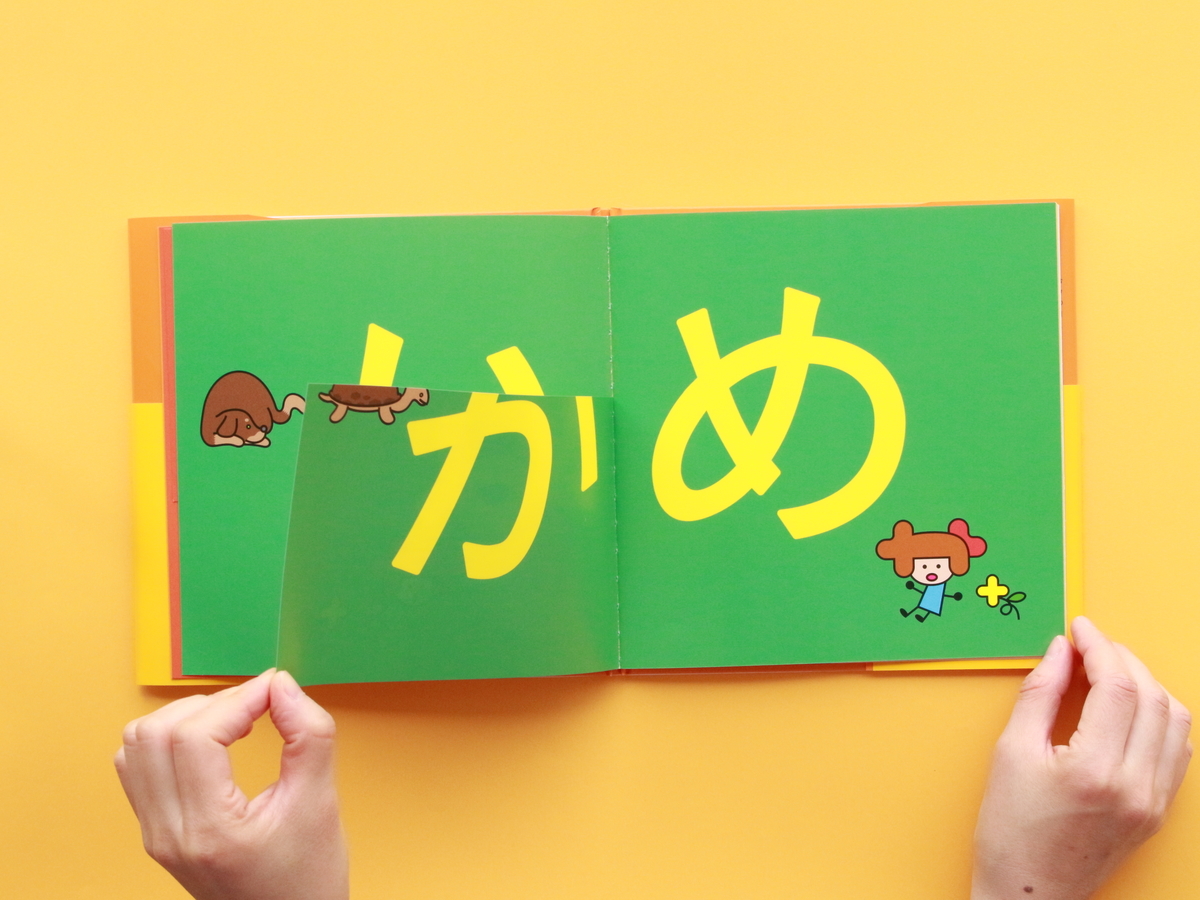
一瞬で文字と意味が変わる! 感覚で感じる面白さ「もじかけえほん かな?」
タイポグラフィの面白さを感覚的に表した絵本、『もじかけえほん かな?』。一部のページが縦や横の半分サイズになっているという、単純なしかけながら、めくるとあっと驚く変化が起こる。
たとえば「さら」。
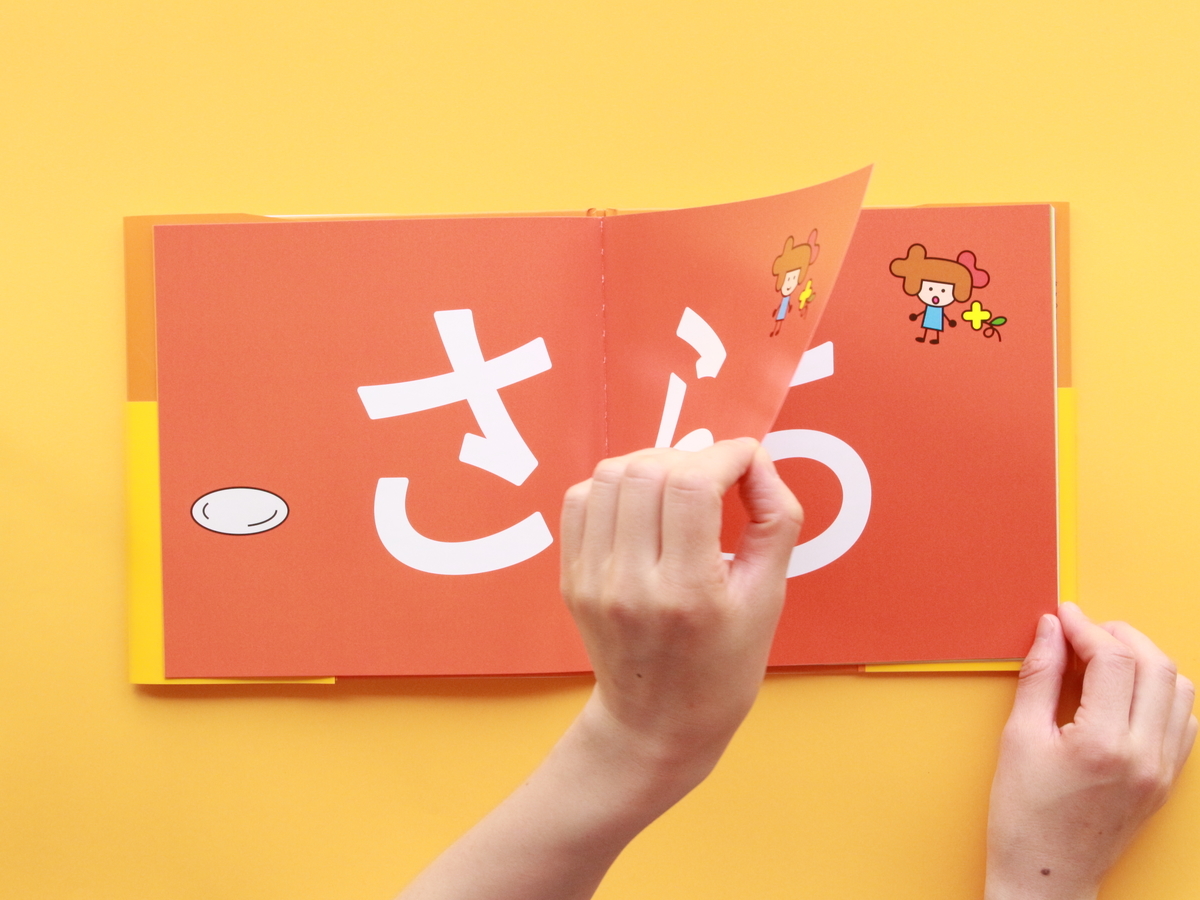
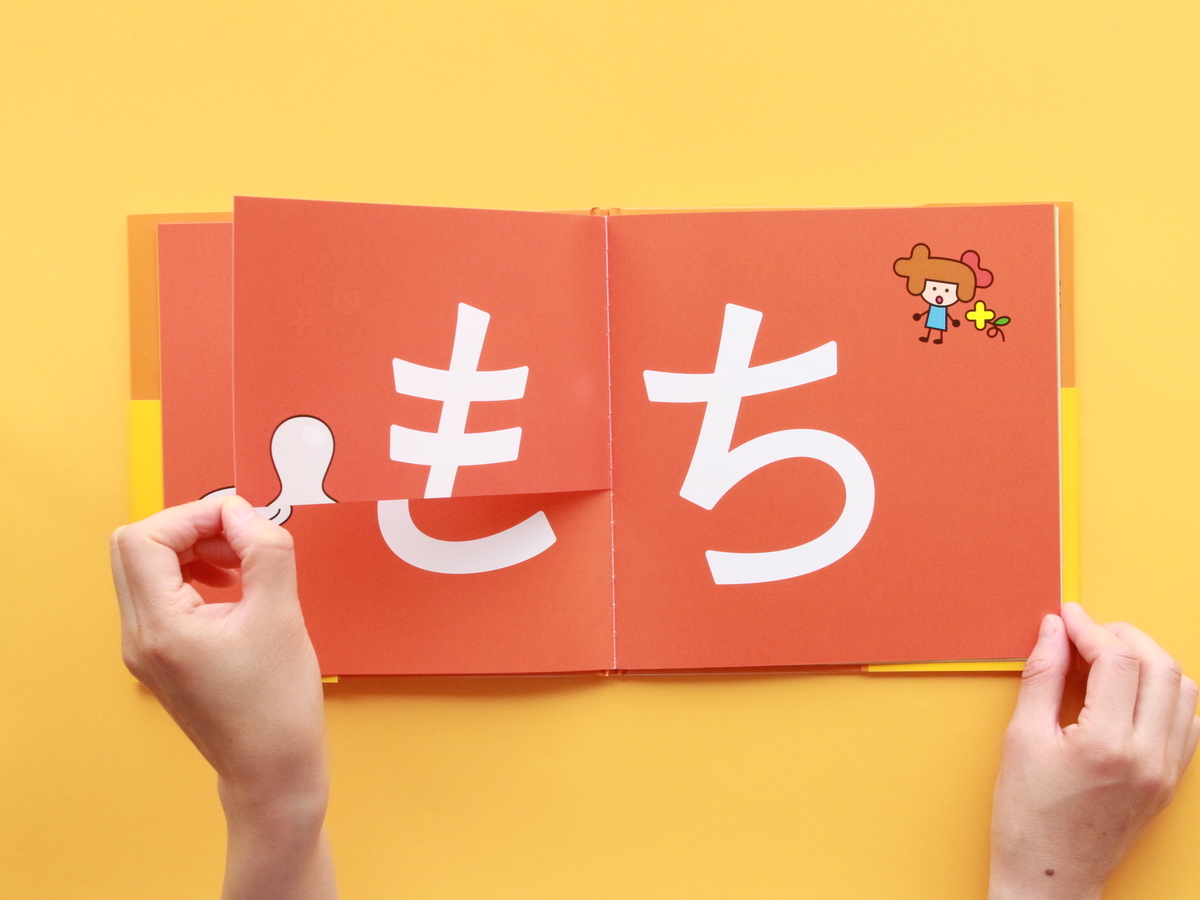
なんと、「もち」に早変わり! 左に描いてある皿の絵も、上にふくらんだ餅に変わっている。
このように、文字の上や下の一部、時には左右の一部を書き換えるだけで、まったく別の文字が出来上がり、意味も変わる。『もじかけえほん かな?』では、作者の大日本タイポ組合の二人が膨大な数の試作の中から選び抜いた、とっておきの言葉を収録している。
タイポグラフィは、子どもも大人も大好き! 何度見ても飽きない「もじかけえほん かな?」
大日本タイポ組合は、秀親さんと塚田哲也さんの二人組。グラフィックや装丁、パッケージデザインなどを数多く手がけている。タイポグラフィの魅力は、年齢を問わず楽しめること。たとえば2018年、塚田哲也さんがツイッターで発信したこのツイートは、4.5万いいねと大きな話題となった。
山手線の新駅「高輪ゲートウェイ」のカタカナ部分が、見事に「門」の字の配置におさめられている。カタカナが入った駅名に賛否の声が上がっていた当時、カタカナのまま見た目を漢字一文字に見せたユーモアあるアイデアは、さまざまな年代の人々から注目された。『もじかけえほん かな?』は、こうしたユニークなタイポグラフィを子ども向けに単純化し、より広い年齢で、何度でも楽しめる形になって生まれた。ひらがなを勉強し始めた子供にもぴったり。